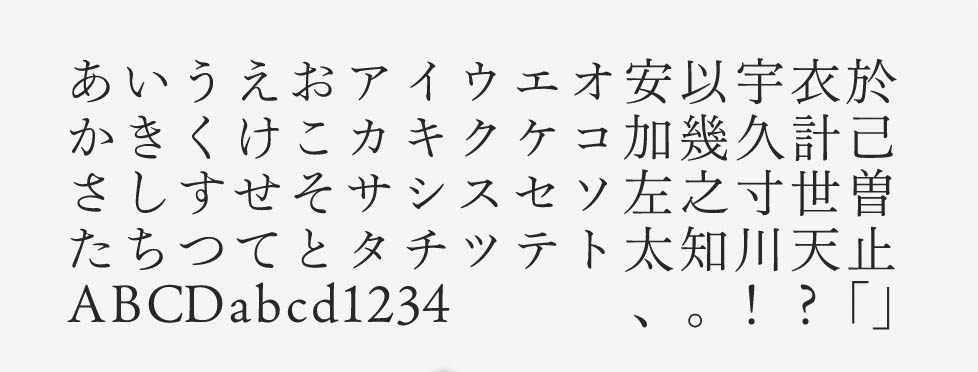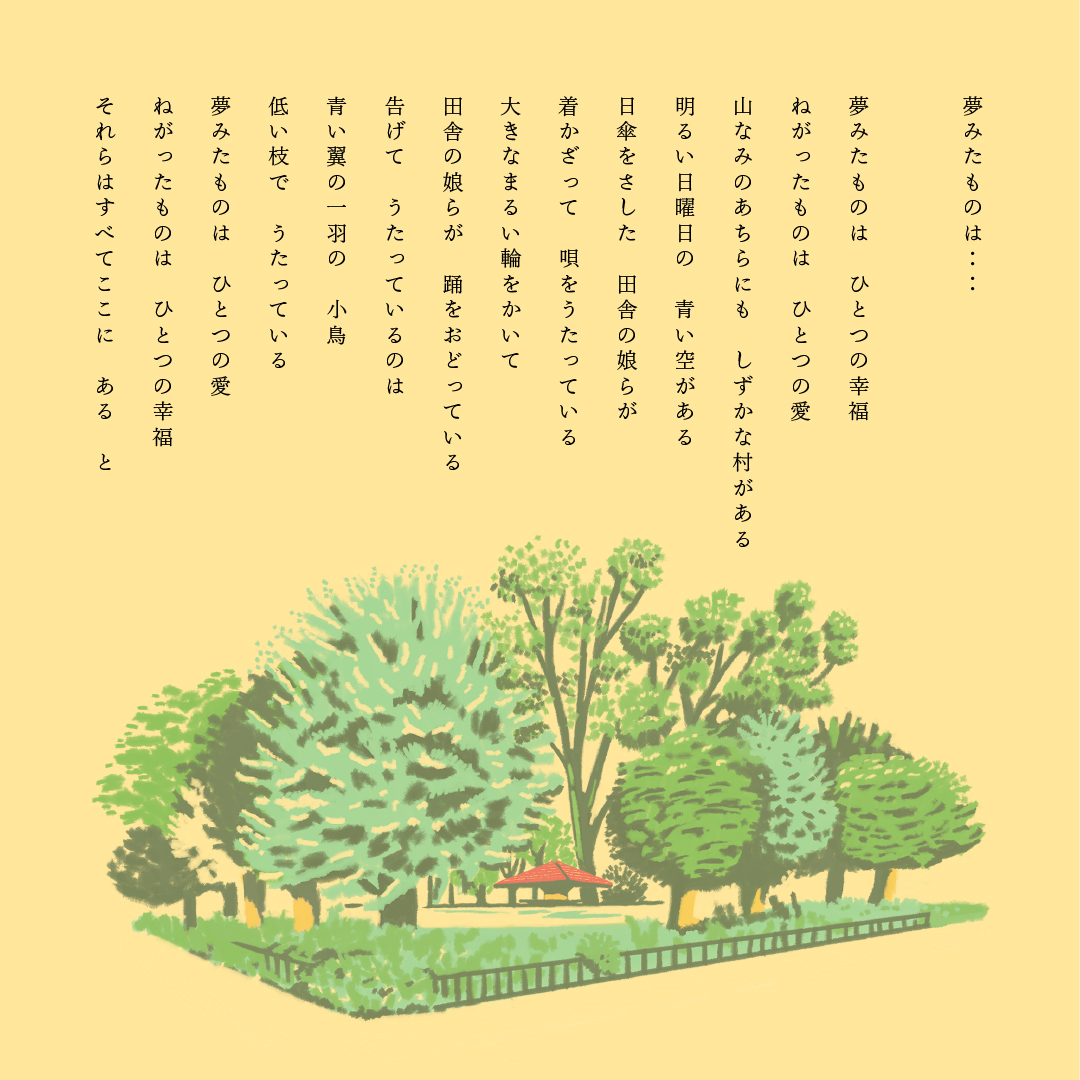
「文游明朝体」について
文游明朝体は「時代をこえる普遍性を具えた造形美と可読性を標榜する日本の明朝体をつくる」というコンセプトにもとづいて作り出されたフォントです。字游工房で開発され、モリサワでの提供は2021年に開始されました。小説などの文学作品で、本文を美しく組むことを目的として開発されています。
「文游明朝体」の特徴
文游明朝体の骨格は、日本での文字の起源などを背景にした伝統的なデザインです。横線が明朝体としてはやや太めであることも特徴で、オフセット印刷での安定感のある “黒み” が実現されています。
ひらがなは平安時代の古筆をもとにしながら設計されており、優雅さを感じさせます。漢字やカタカナも、それぞれ固有の骨格が尊重されていて「漢字は漢字らしく」「ひらがなはひらがならしく」「カタカナはカタカナらしく」デザインされたフォントです。
作例は基本に忠実に縦組みでデザインしましたが、文游明朝体のように普遍的かつ丁寧に設計された美しい書体は、横組みでも問題なく組めそうです。ルールやセオリーに縛られることを恐れず、自由な発想で使うとまた新しい視点やテクニックが生まれるでしょう。